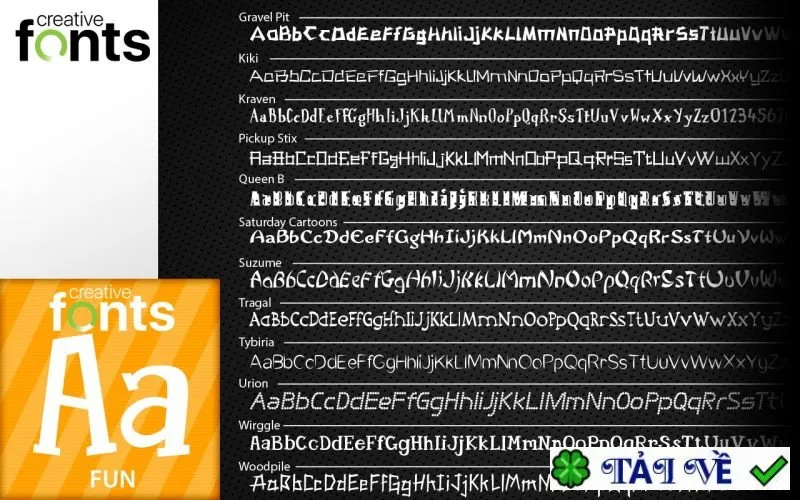
Bạn đang tìm kiếm những nét độc đáo cho dự án sáng tạo của mình? Bộ sưu tập Summitsoft Wonderful Fonts Collection 2022 mang đến hàng loạt font chữ nghệ thuật chuyên nghiệp, được tuyển chọn kỹ lưỡng theo từng chủ đề hấp dẫn như Khoa học viễn tưởng ?, Thể thao , hay Hài hước ?. Với định dạng OpenType sắc nét, các font chữ này không chỉ dễ dàng sử dụng trên mọi phần mềm ? mà còn giúp ý tưởng của bạn trở nên sinh động và cuốn hút hơn bao giờ hết. Nâng tầm thiết kế của bạn với bộ sưu tập font chữ độc đáo này nhé! ?
Tổng quan về Bộ sưu tập Phông chữ Summitsoft Wonderful Fonts Collection
Summitsoft Wonderful Fonts Collection 2022 là một tuyển tập ấn tượng gồm các phông chữ độc đáo, được thiết kế chuyên nghiệp. Bộ sưu tập này mang đến sự mới lạ và độc đáo, khác biệt so với các phông chữ truyền thống, đồng thời là một bổ sung giá trị cho bất kỳ bộ sưu tập phông chữ nào. Tuyển tập các phông chữ sáng tạo này bao gồm các mẫu độc đáo, được tuyển chọn kỹ lưỡng và phân loại theo từng chủ đề riêng biệt.
Toàn bộ các phông chữ trong bộ sưu tập đều tuân thủ chuẩn OpenType, tiêu chuẩn công nghiệp được phát triển bởi Microsoft và Adobe. Nhờ đó, các phông chữ luôn hiển thị sắc nét và rõ ràng trên mọi kích thước hiển thị. Mỗi phông chữ sáng tạo đều bao gồm bộ ký tự đầy đủ, hỗ trợ các ký hiệu quốc tế, ngôn ngữ nước ngoài và các ký tự đặc biệt.
Các loại phông chữ có sẵn:
- Phông chữ Khoa học viễn tưởng
- Phông chữ Vui nhộn
- Phông chữ Thể thao
- Phông chữ Tuyệt vời
- Phông chữ Trò chơi
- Phông chữ Truyện tranh